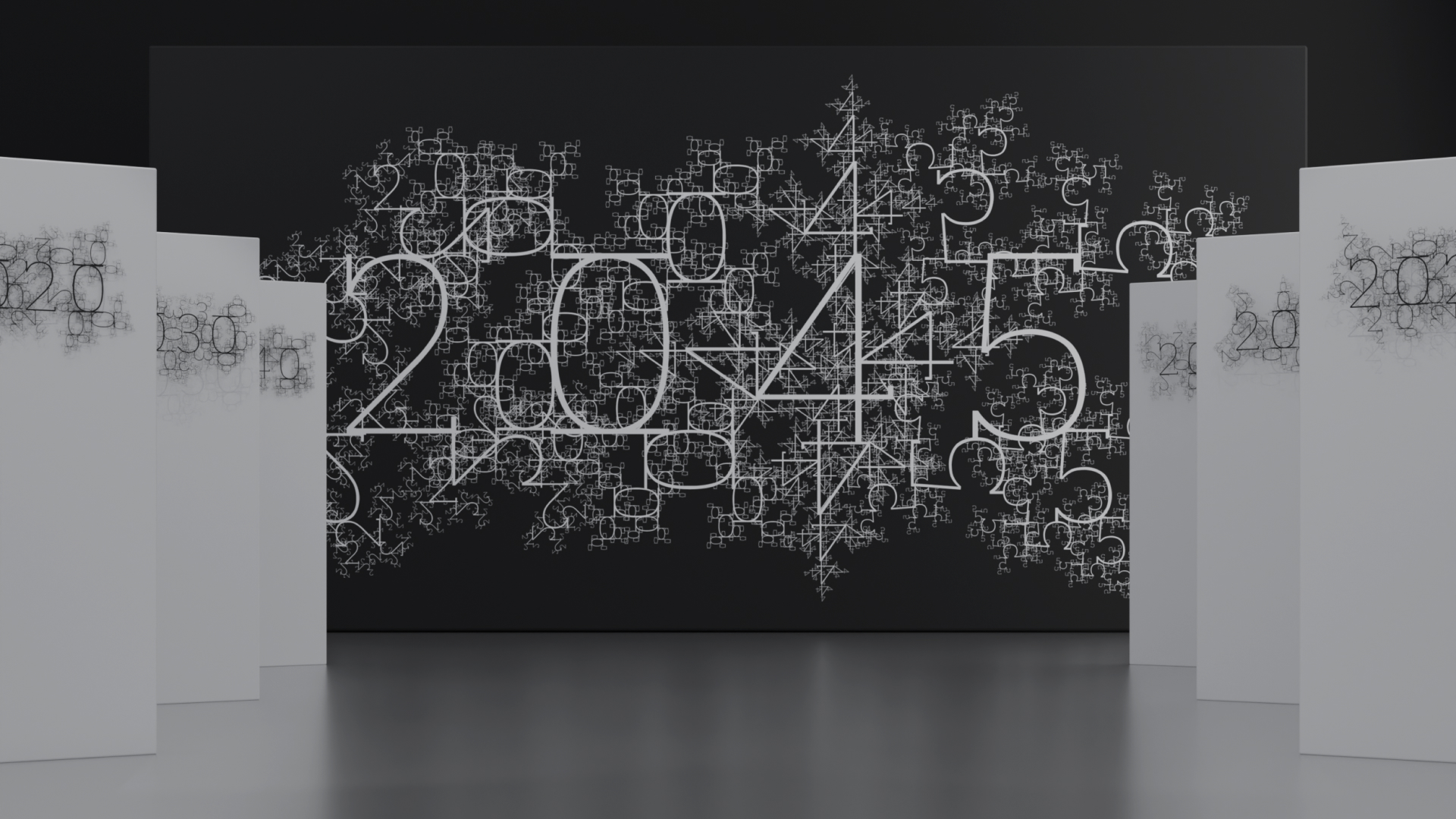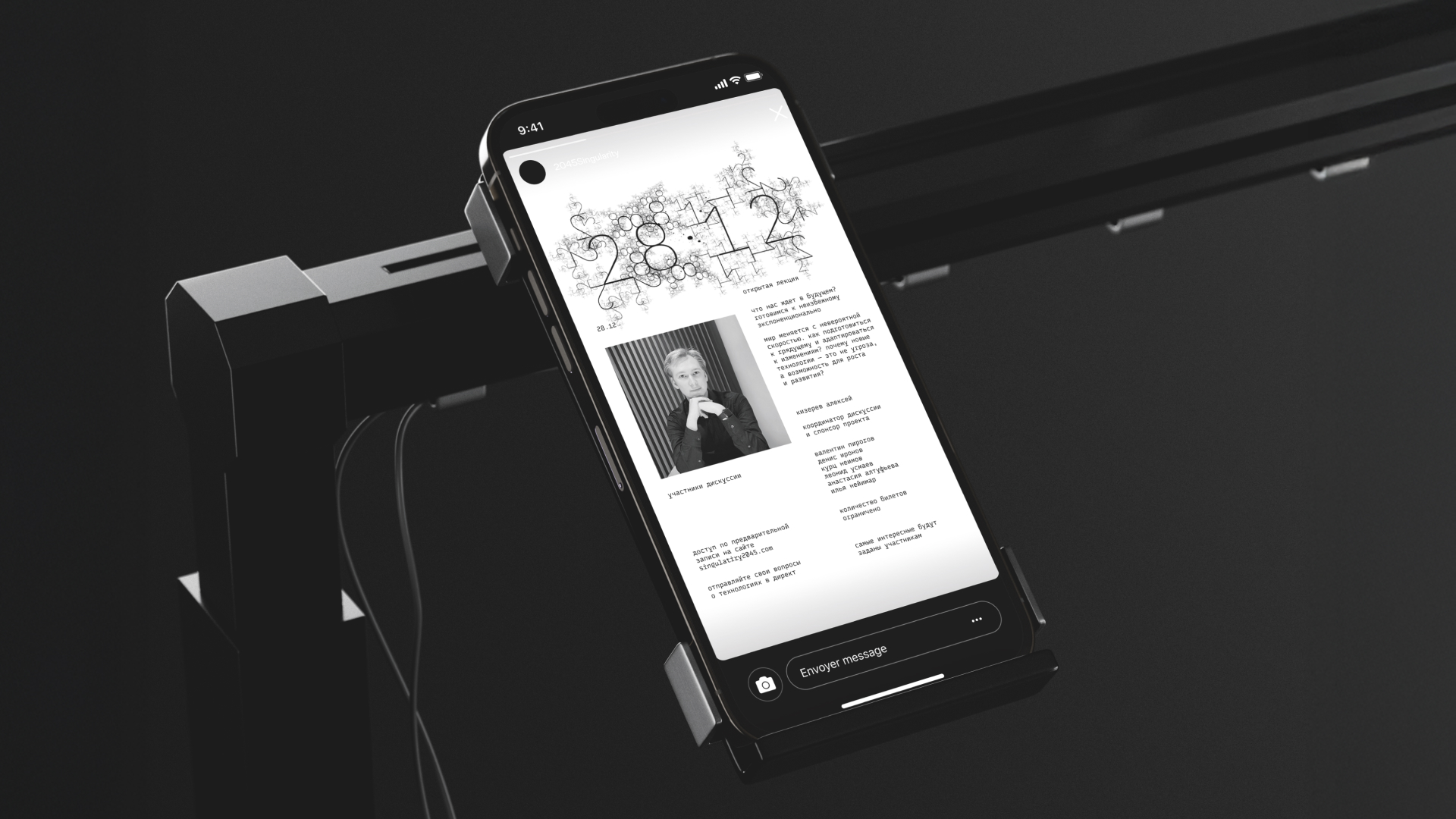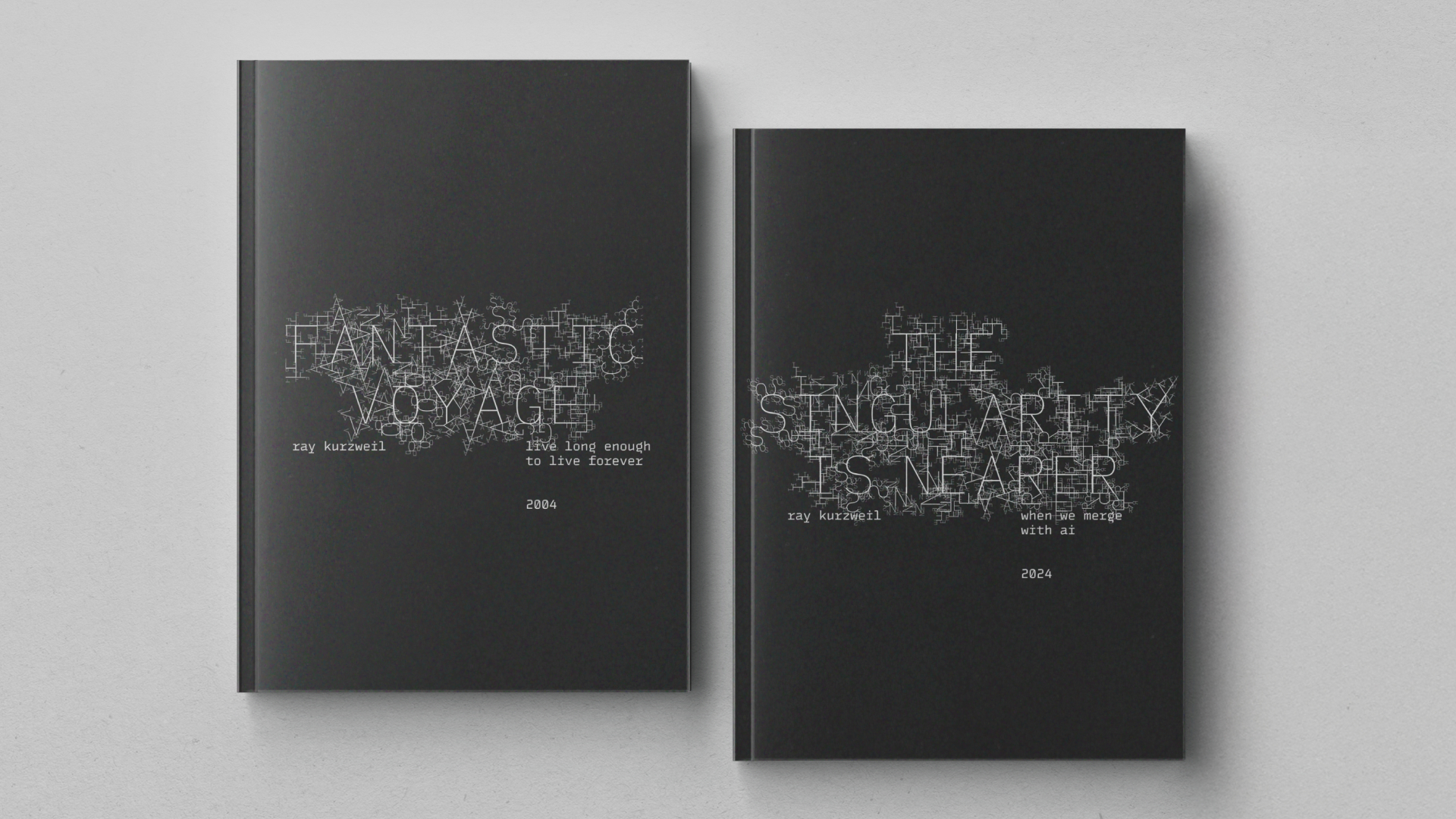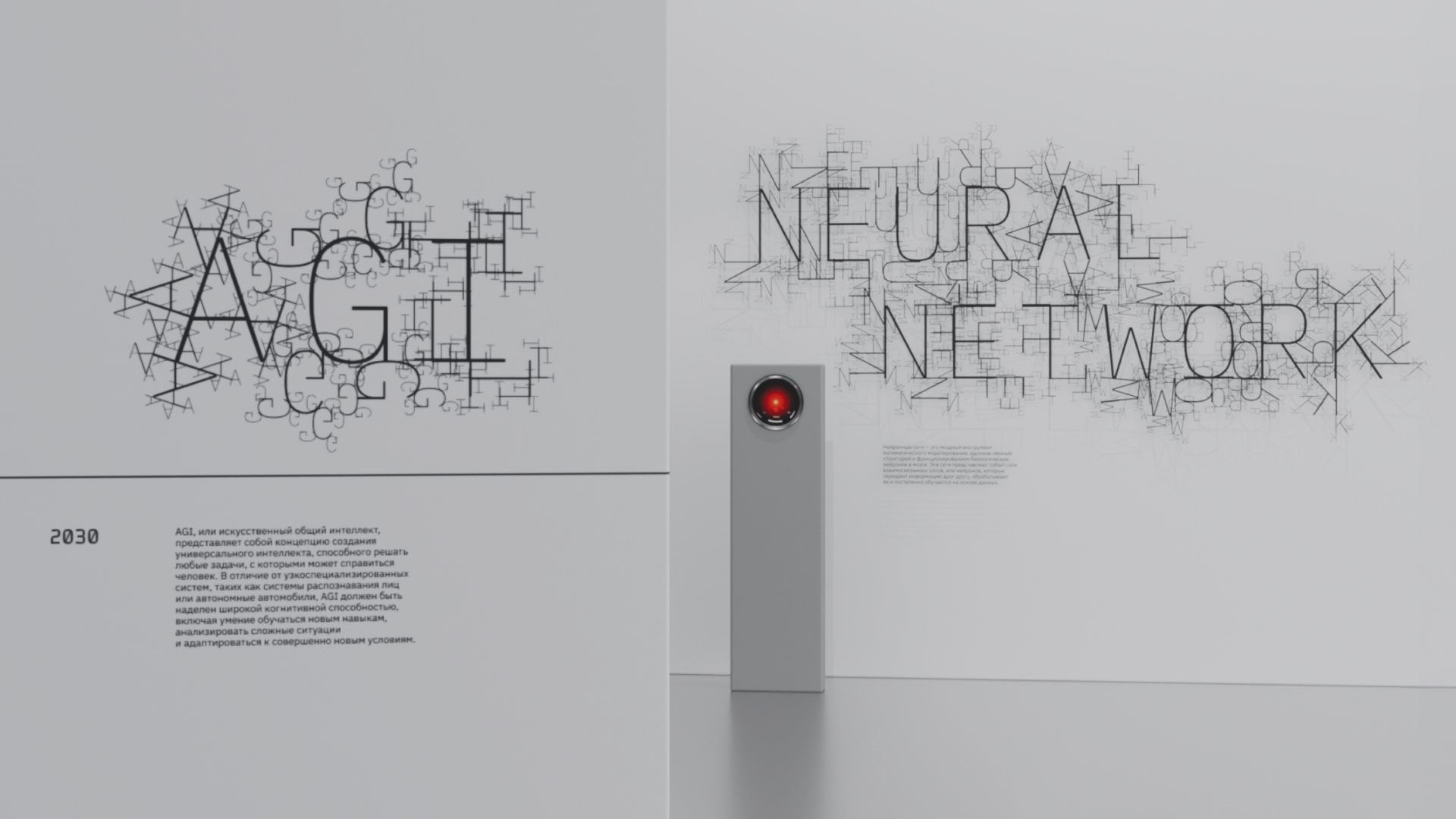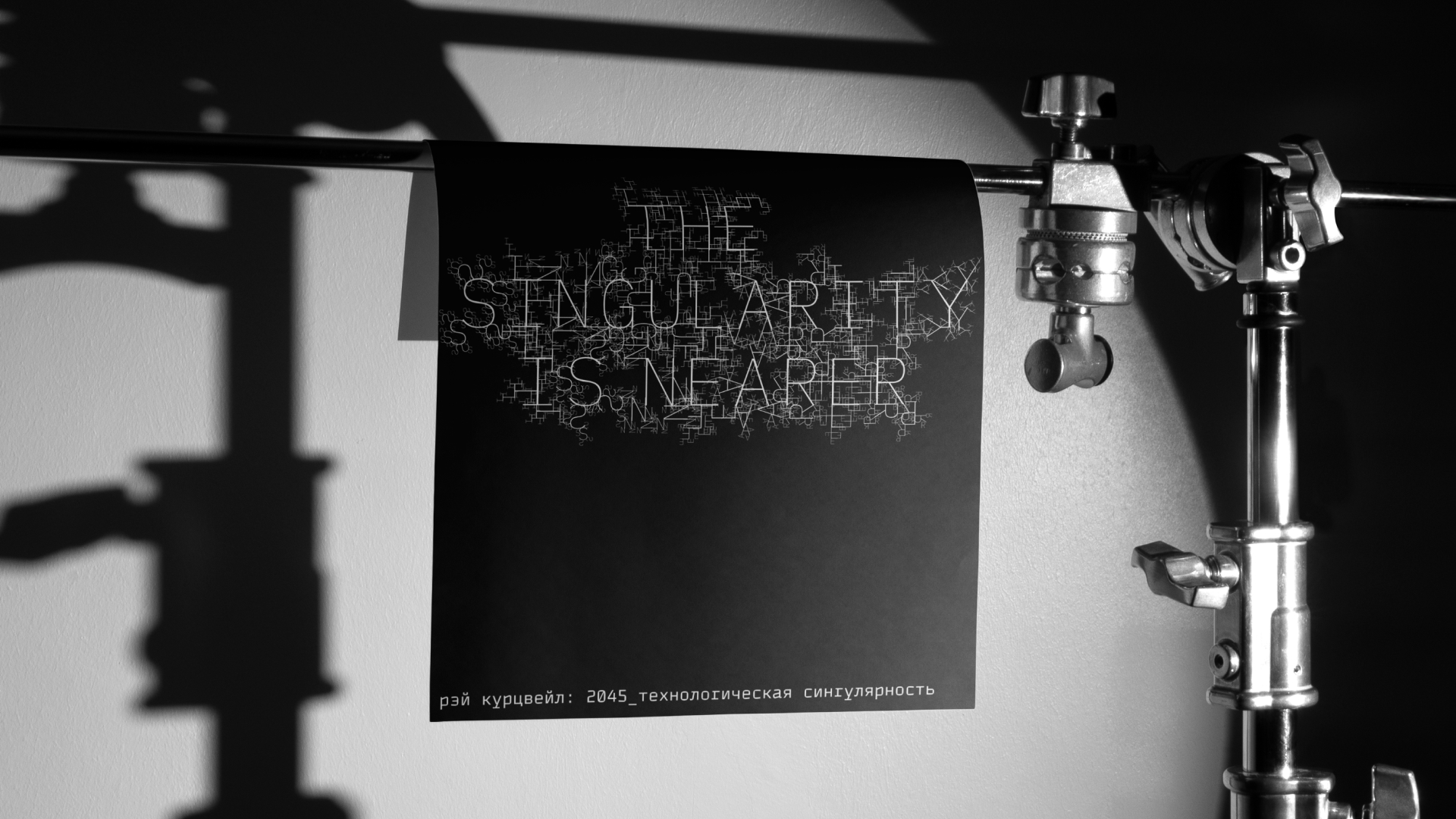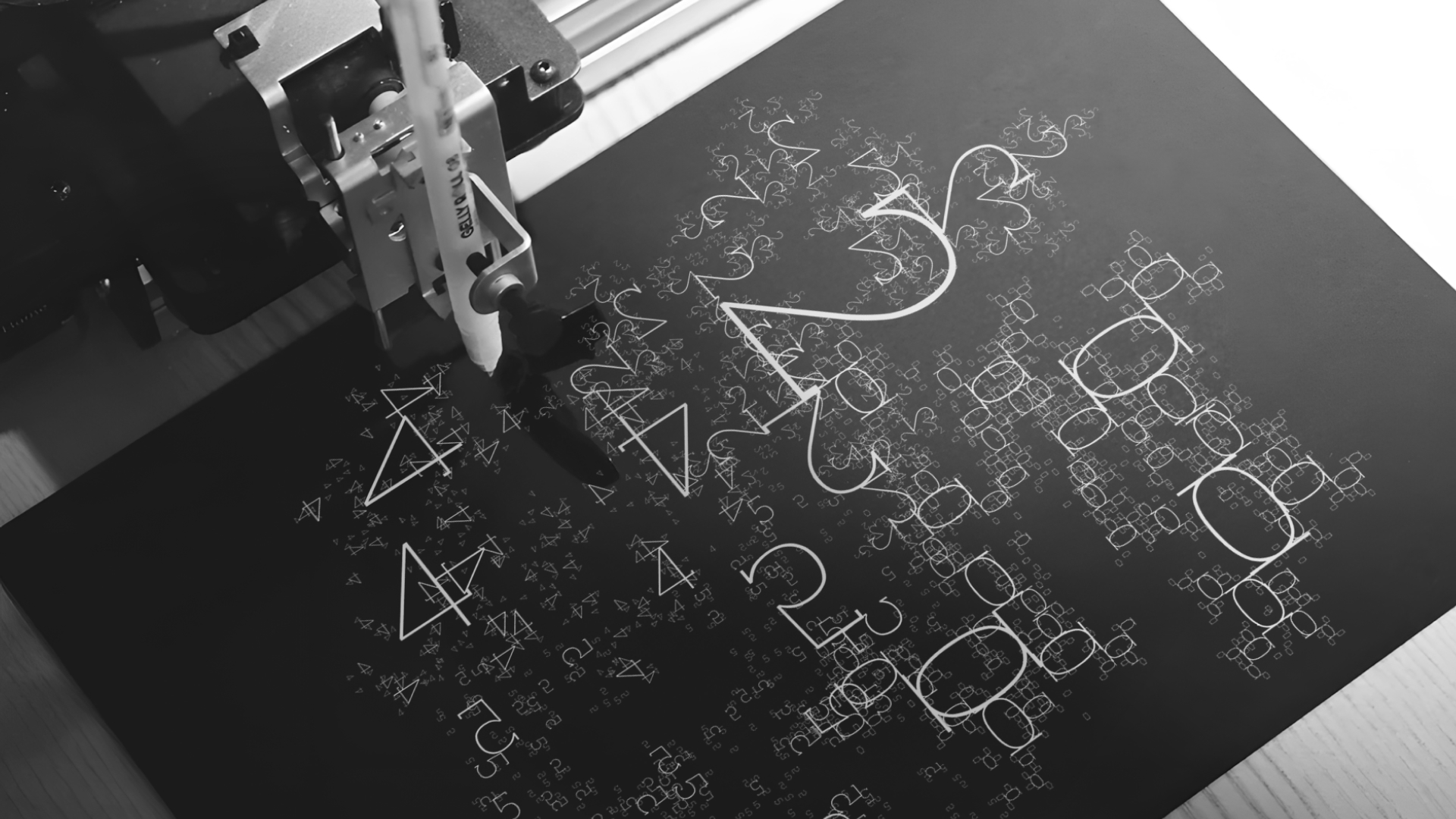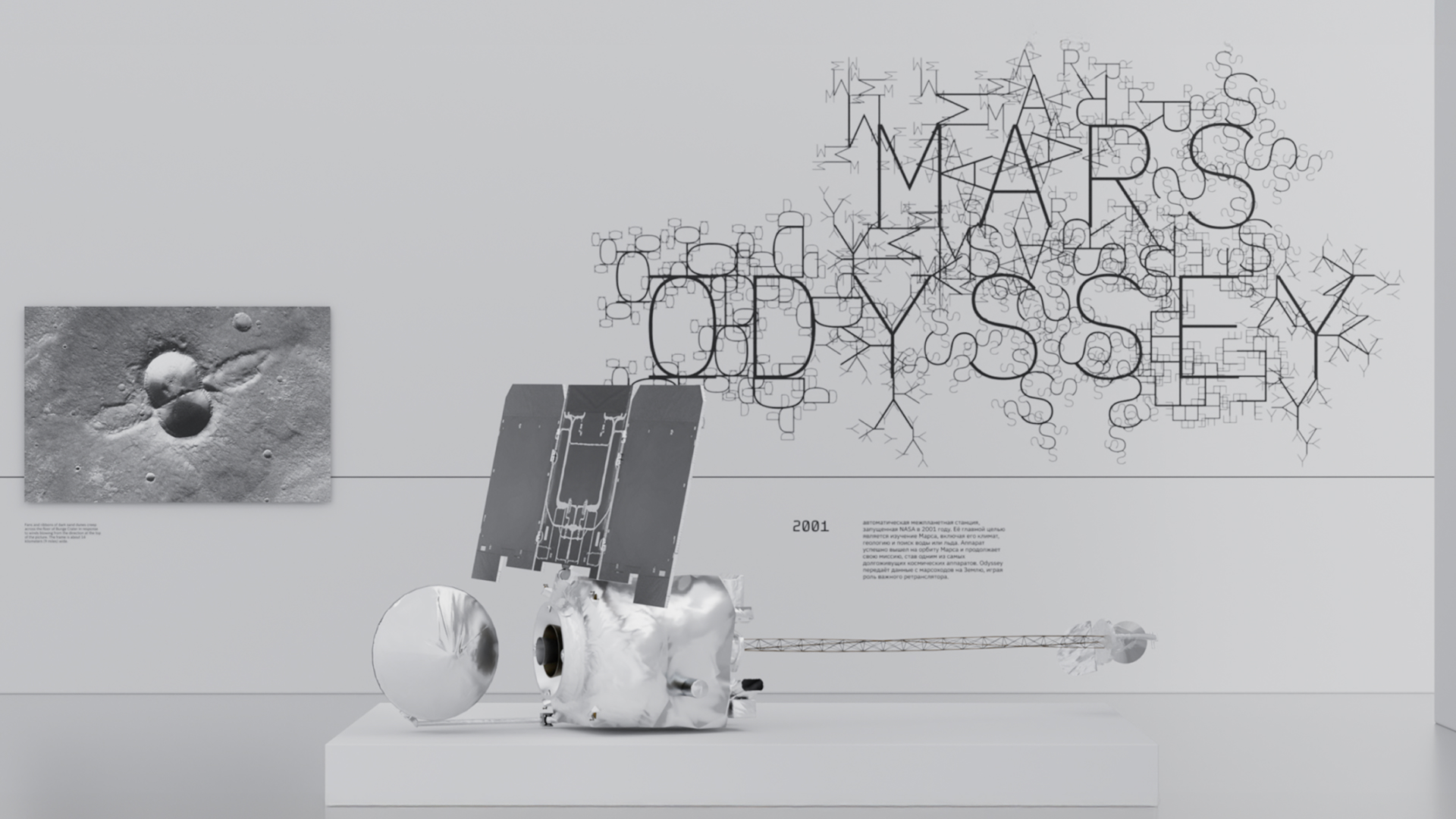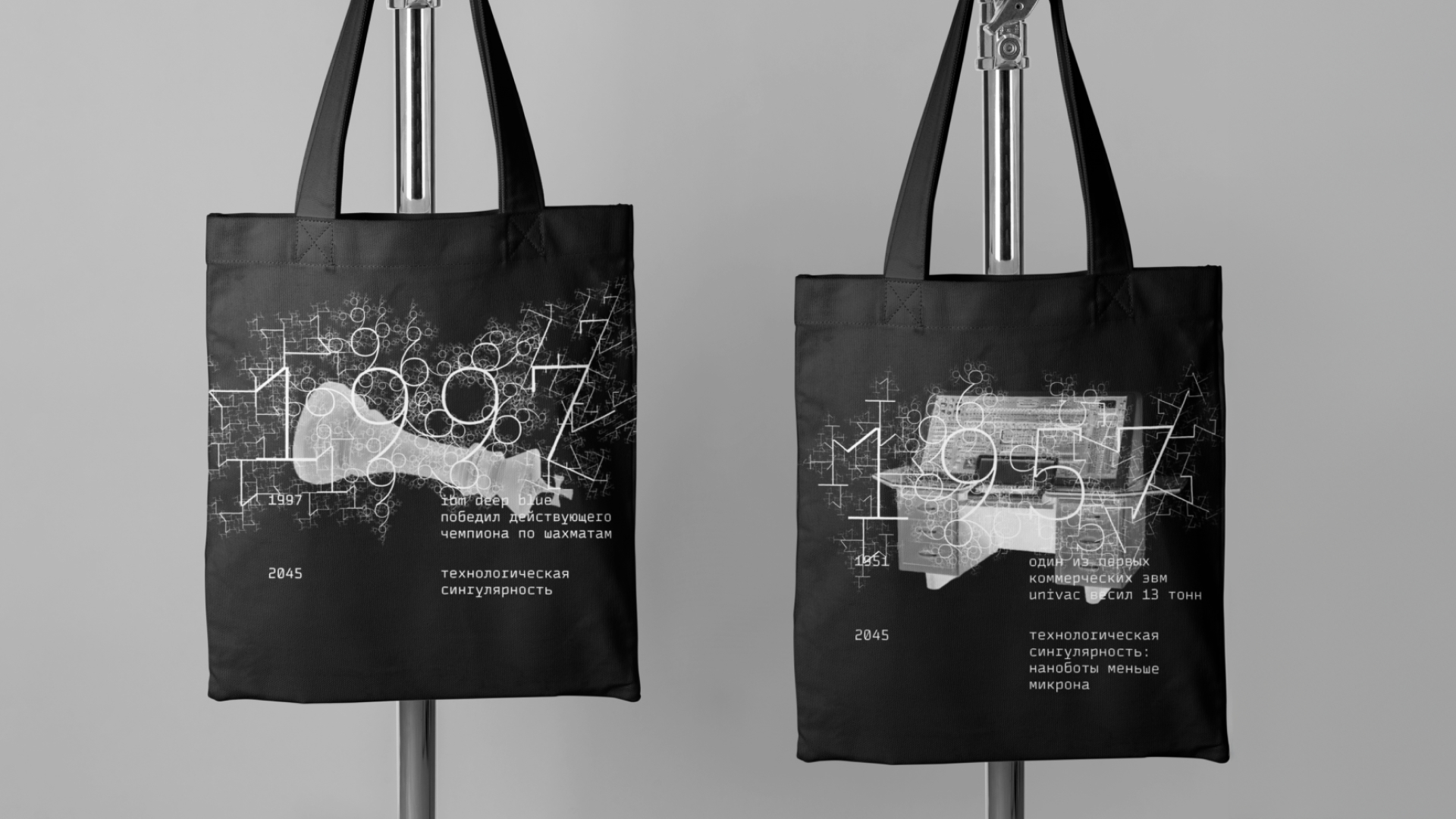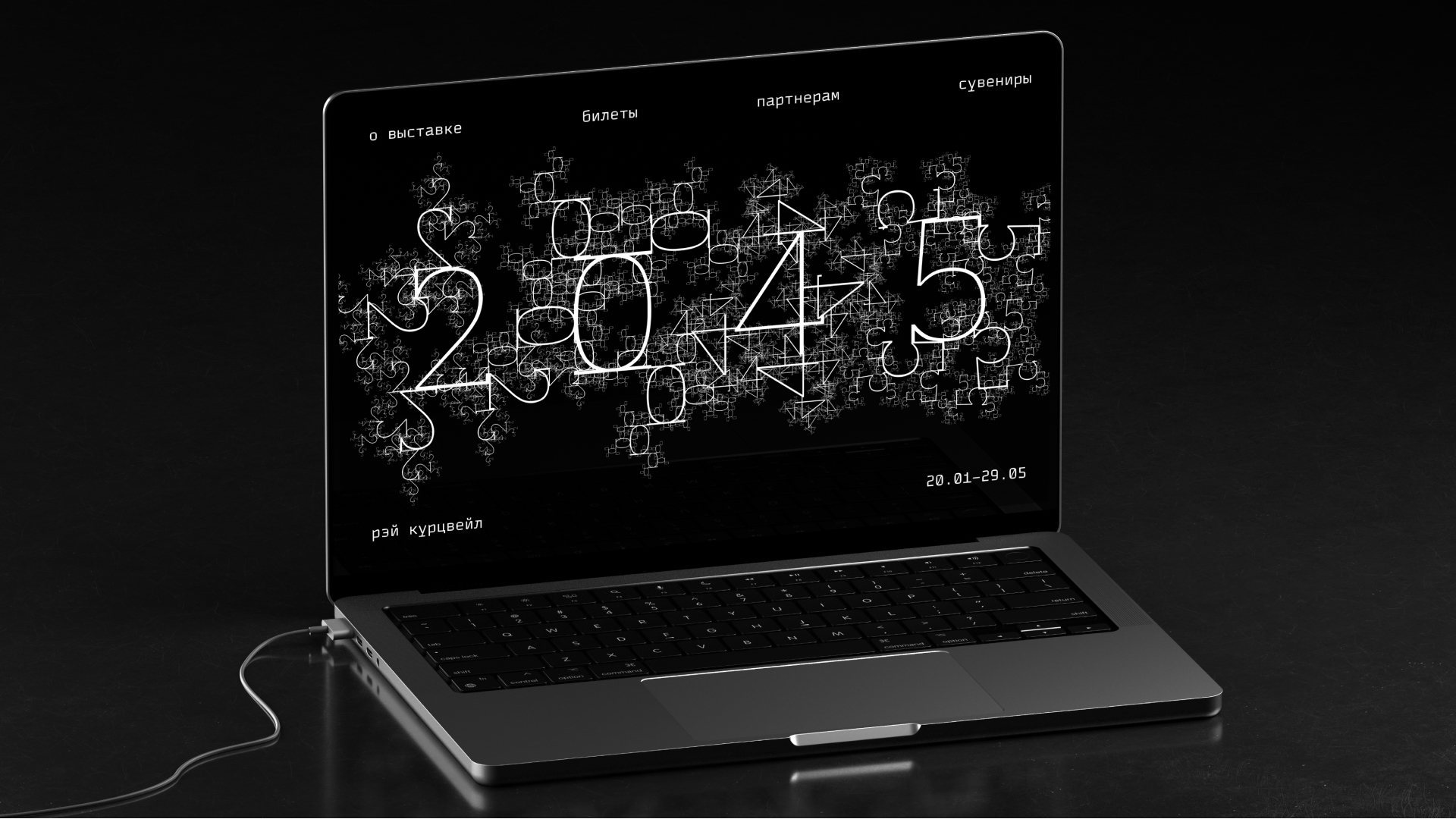
Экспериментальный шрифт
шрифт 2045_технологическая сингулярность
Фрактальный шрифт, созданный для концепции айдентики выставки, посвященной развитию информационных технологий вплоть до 2045 года. По мнению футуролога Рэймонда Курцвейла именно тогда наступит технологическая сингулярность.
Шрифт создан с помощью специального кода на Processing. Такое решение позволяет передать нарастающую сложность и ускорение технологического прогресса, отражая идеи экспоненциального развития.